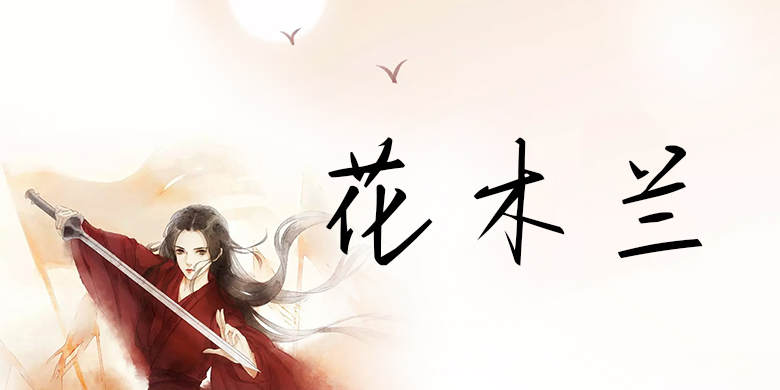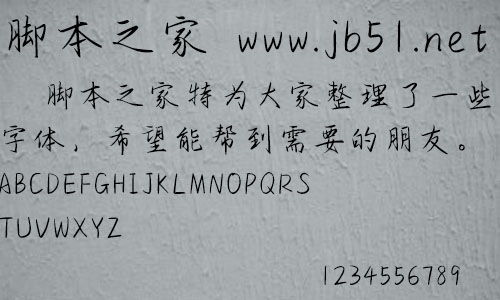
方正手跡-花木蘭由方正字庫羅曉康設計師出品的藝術字體,筆法細膩,結構嚴謹,一點一畫間才情橫溢,適合應用于藝術設計、平面宣傳設計、網(wǎng)頁設計,書法等領域。
花木蘭這款字體筆法細膩,結構嚴謹,一點一畫間才情橫溢,韻味悠長極具內涵。適用于文藝類的書刊、品牌廣告和產(chǎn)品包裝設計,以及社交網(wǎng)絡的個性化用字。。。